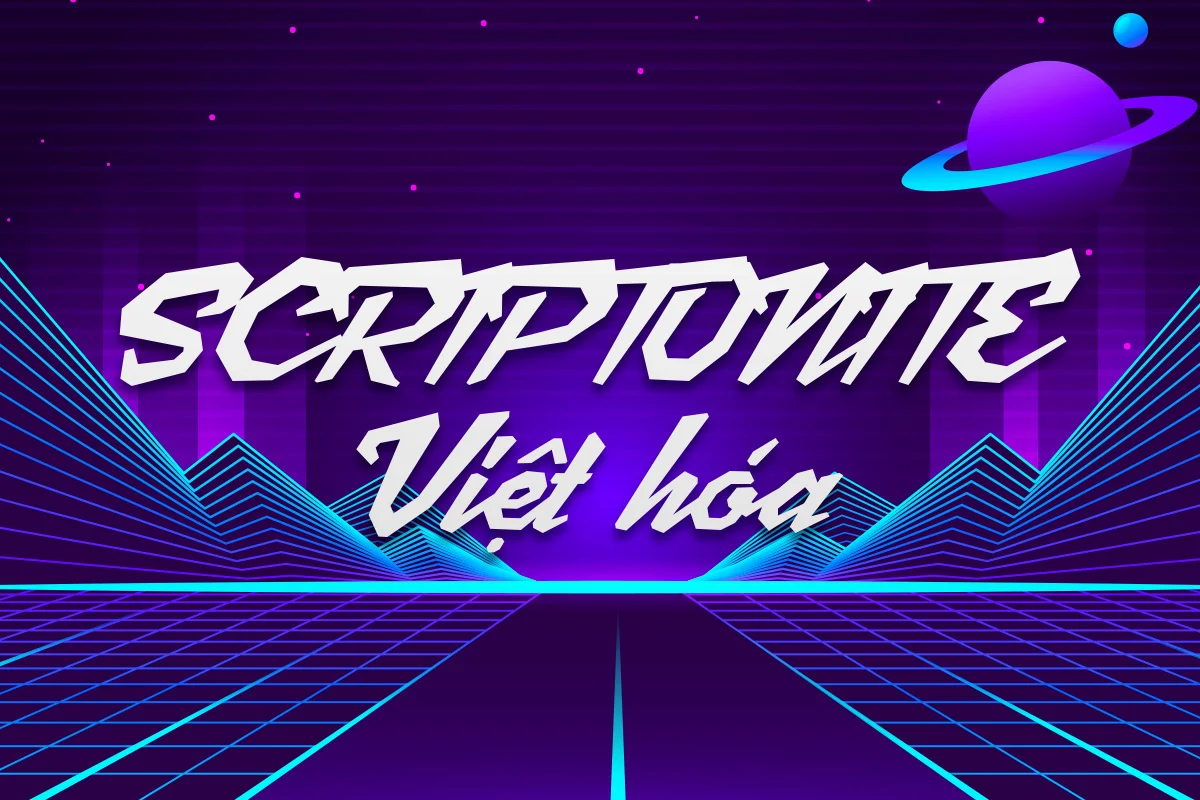
SCRIP TONITE là một font chữ mang đậm tinh thần cyberpunk – góc cạnh, nổi loạn và đầy năng lượng. Với các nét cắt sắc sảo, cấu trúc nghiêng ngả mạnh mẽ và đường nét gãy khúc ấn tượng, font này như thể bước ra từ một thế giới tương lai nơi ánh đèn neon và công nghệ hòa quyện trong bóng tối đô thị. SCRIP TONITE rất phù hợp để sử dụng trong các tiêu đề game, poster sự kiện EDM, bìa truyện khoa học viễn tưởng, hoặc bất kỳ dự án nào cần một chất riêng đậm nét nổi loạn, mạnh mẽ và hiện đại. Phiên bản Việt hóa được tinh chỉnh tỉ mỉ, giữ nguyên chất "chất chơi" nguyên bản và hỗ trợ đầy đủ dấu tiếng Việt, mang đến trải nghiệm thị giác trọn vẹn cho người dùng trong nước.